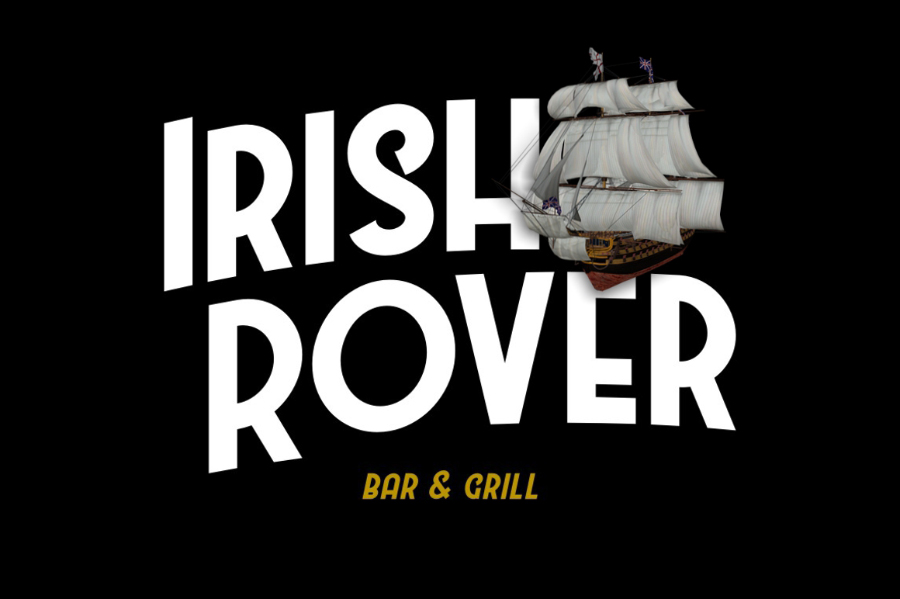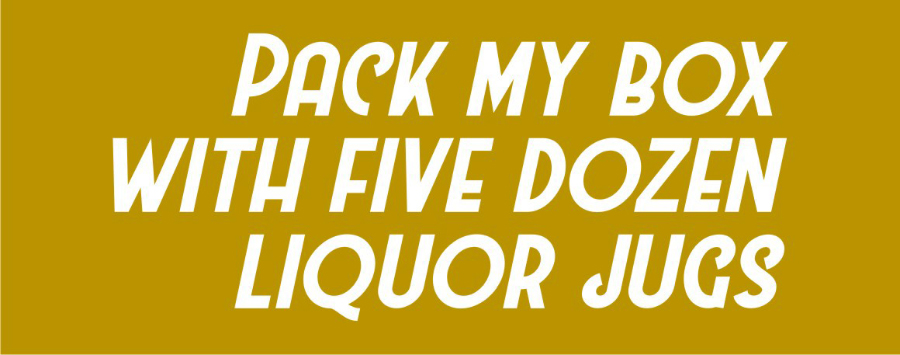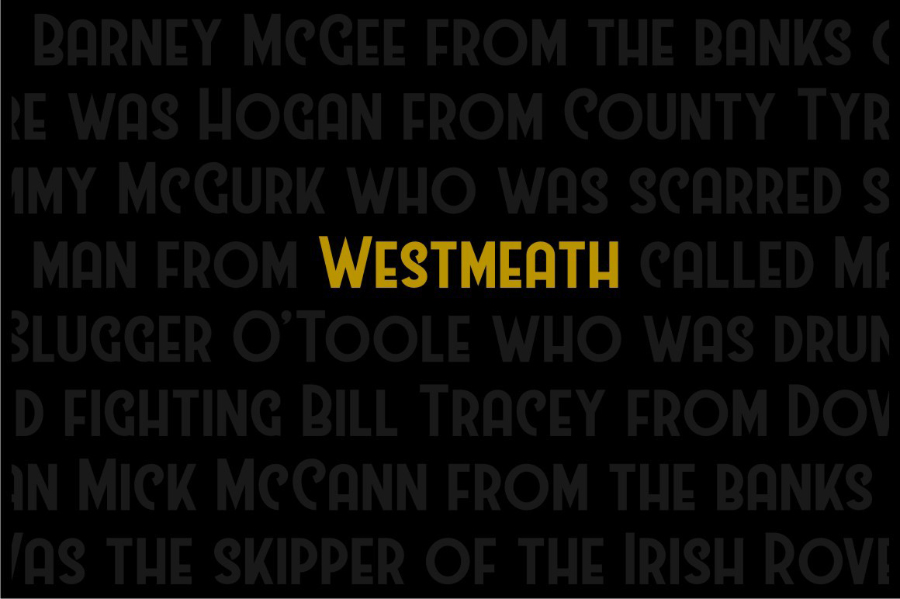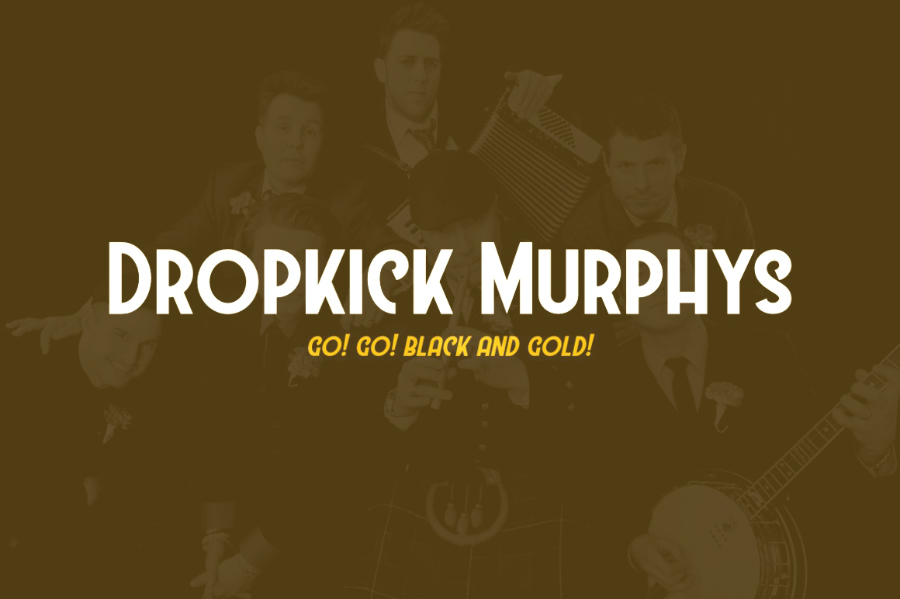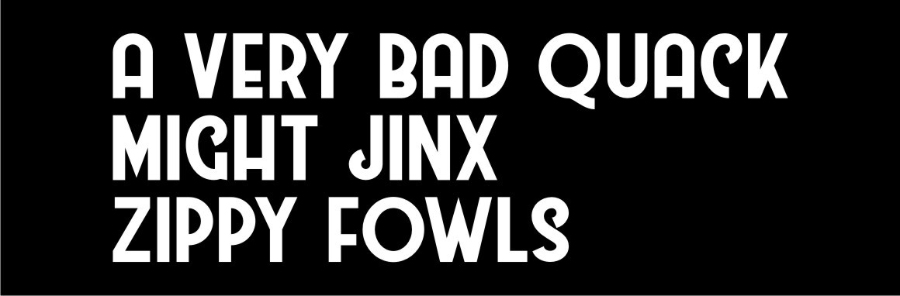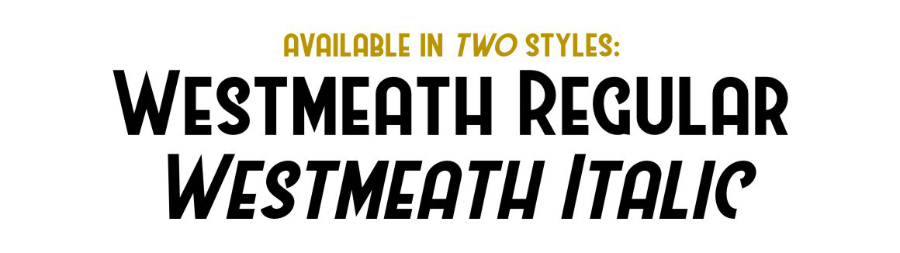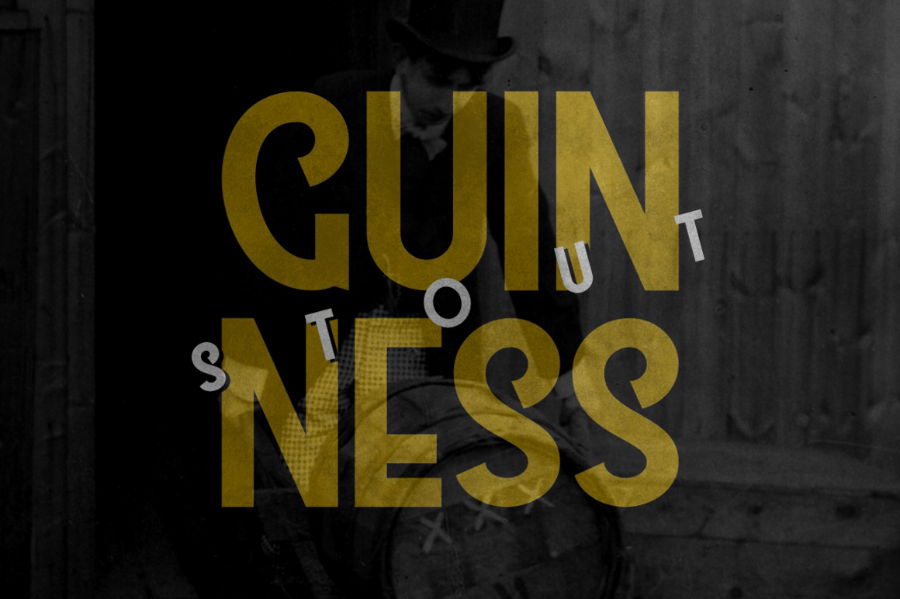
Westmeath自由字体
Twicolabs设计乐意向您介绍新的字体; Westmeath自由字体。一个干净的无衬线字体,有点胖,但仍然看起来性感,而艺术装饰是。它也代表了经典或复古但时尚的字体外观。 Westmeath有两种风格的Regular和Italic。这两种风格的组合将是伟大的任何复古的设计,如海报,理发店和餐厅标志,以及品牌。